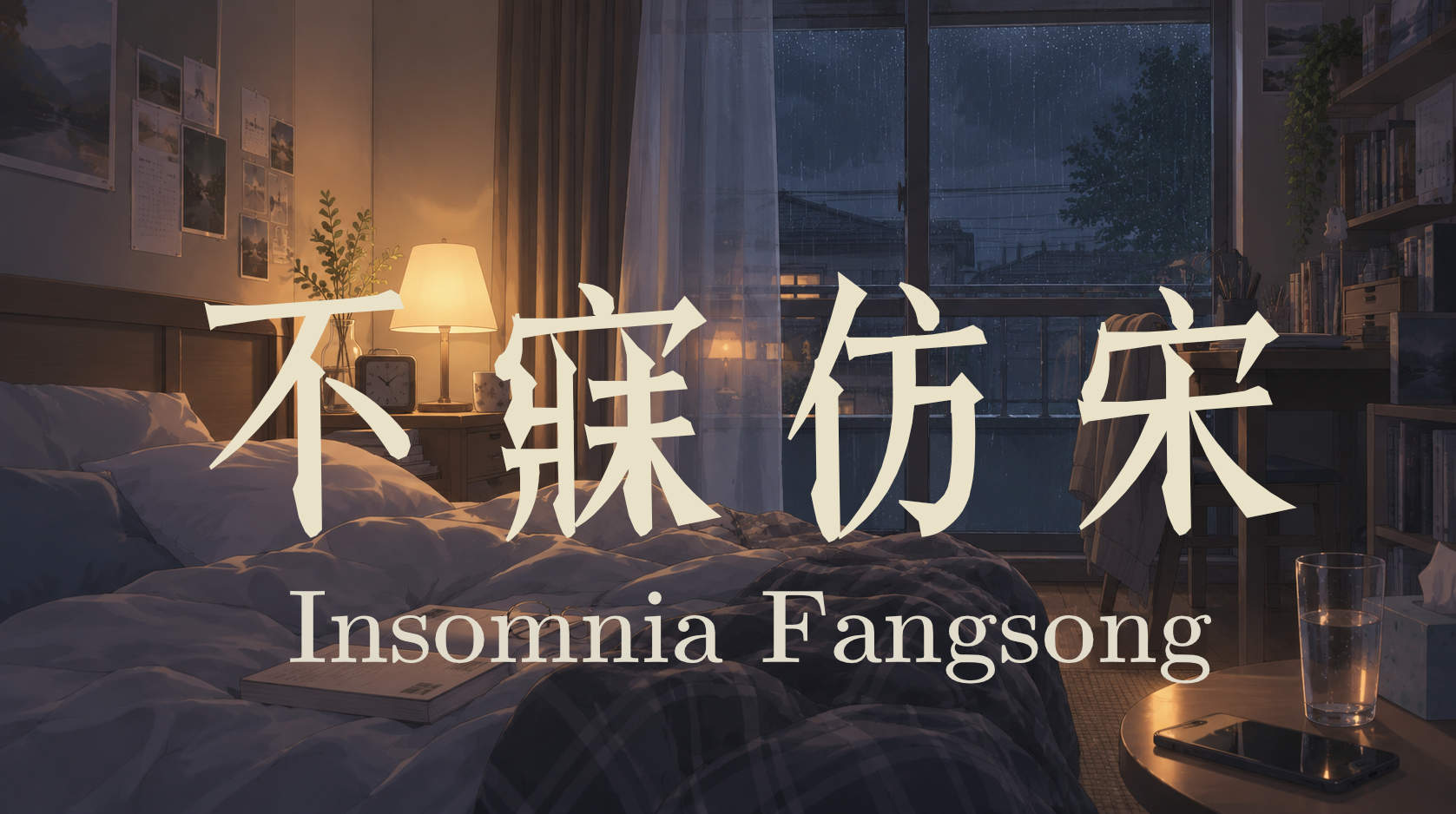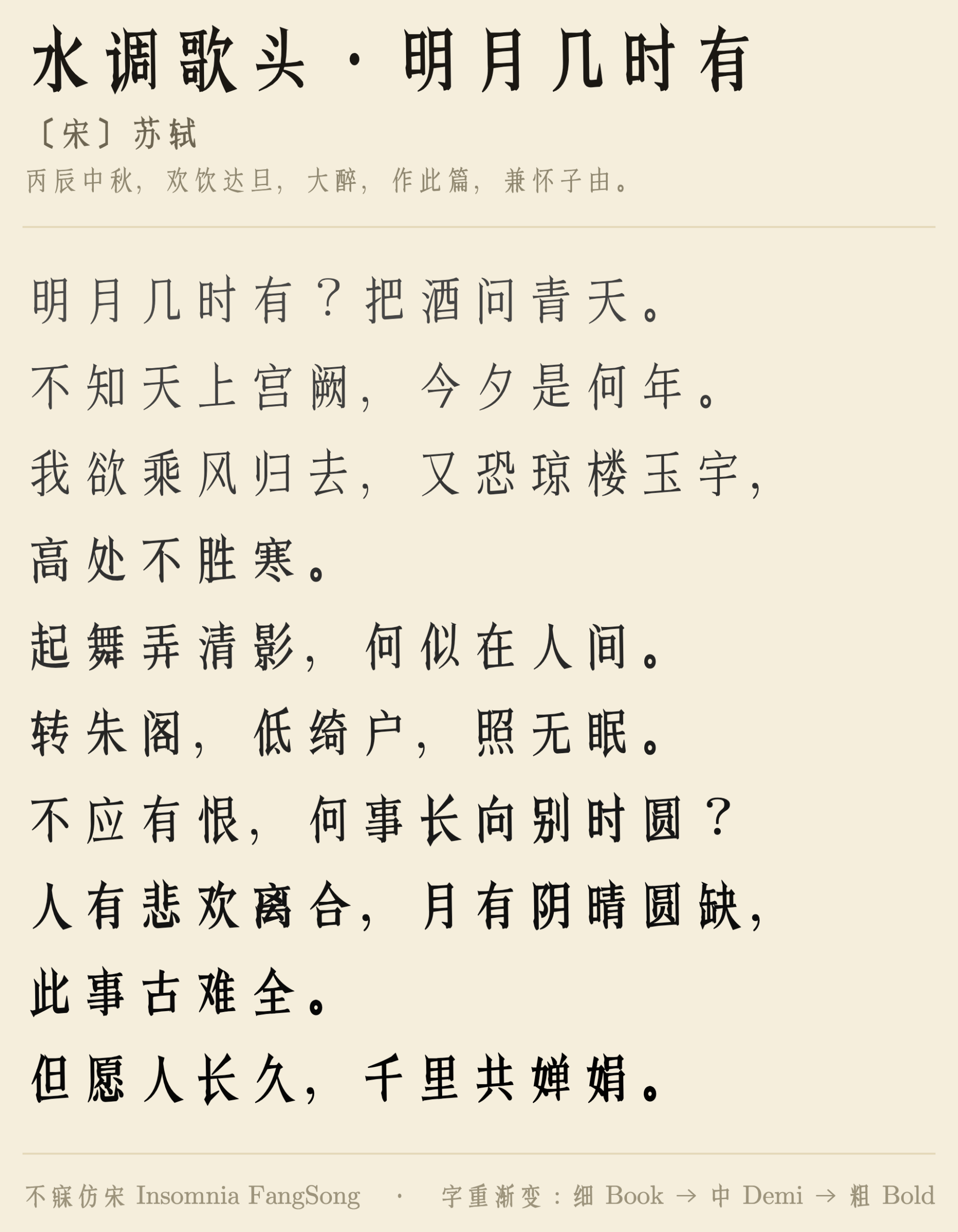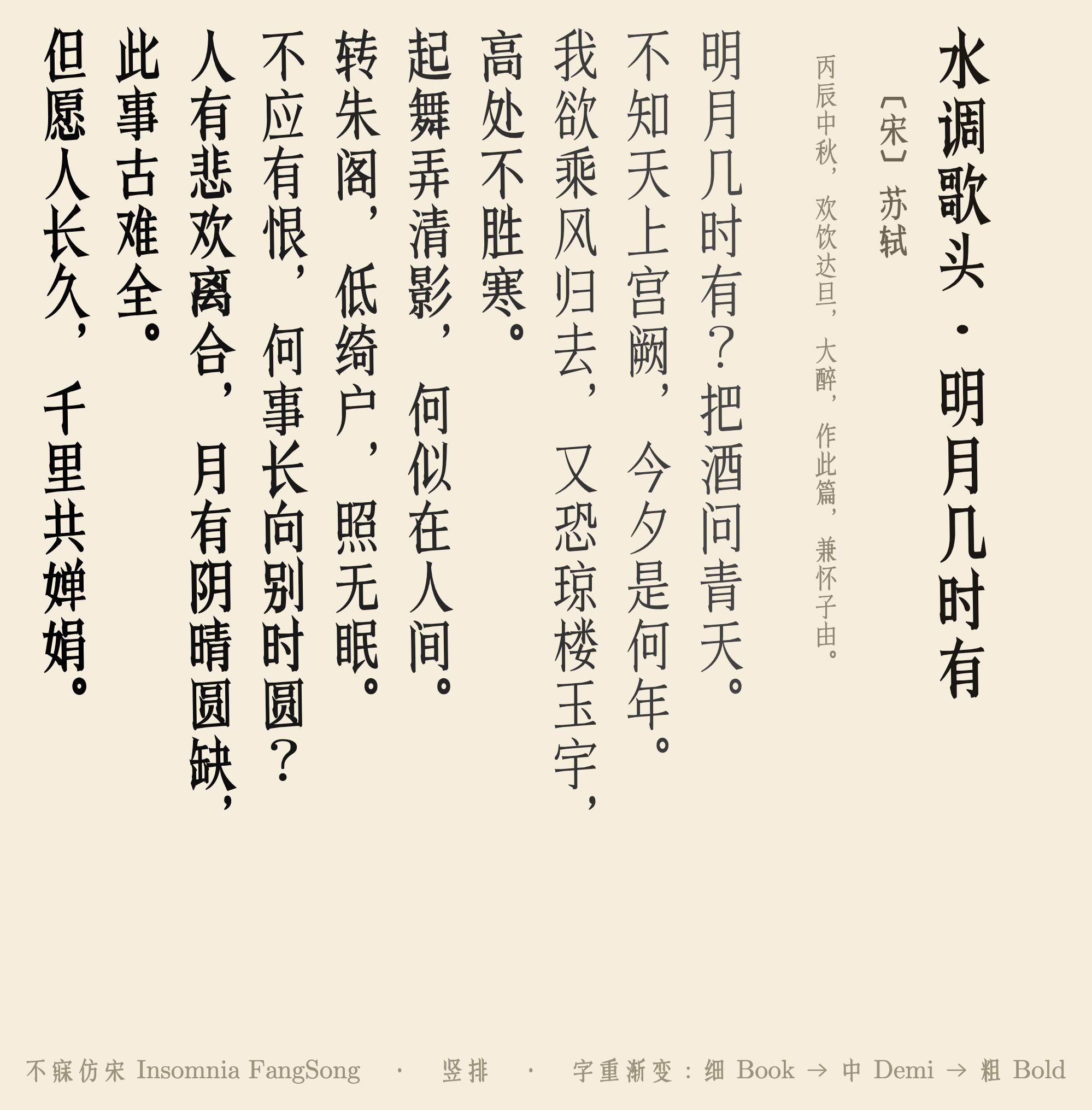
不寐仿宋 一款开源的仿宋体(日文称「宋朝体」)。以 HZ 宋朝 为基底, 补齐简体中文缺字,并把全部 GB2312 汉字改为大陆国标(G 源 / 新字形)字形。
不寐仿宋 HZ 宋朝/HZ Socho 是由 字形维基(GlyphWiki) 的汉字数据生成的开源仿宋体(宋朝体);其汉字以日本字形为准,不符合中国大陆书写规范。
《不寐仿宋》在保留原有仿宋风格的基础上,将简体中文部分调整为大陆标准。
字体特性
全 GB2312 大陆字形:HZ 宋朝自带的约 3100 个日式(JIS)汉字已改为大陆简体标准,另补齐 2238 个缺失的简体字;GB2312 一二级共 6763 字全部为国标字形。
三字重:Book 400 / Demi 600 / Bold 700
支持竖排:保留 vhea / vmtx 与 GSUB vert / vrt2,竖排度量已校正。
兼容性好:TrueType(glyf)轮廓、非 CID 结构,可在 CorelDRAW 等软件正常显示中文。
补上间隔号 ·:HZ 宋朝缺 ·(U+00B7)与 ‧(U+2027);已用字体自带的仿宋中点补齐,随字重自动变粗。
其余非汉字(拉丁 / 希腊 / 西里尔 / 假名 / 符号 / 标点)沿用 HZ 宋朝,未改动。